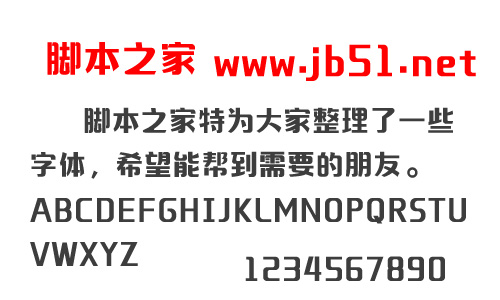
字心坊紳士黑字體
字心坊紳士黑字體是一款剛?cè)岵?jì)的粗黑體。設(shè)計(jì)初衷是一款力量感較強(qiáng)的同時(shí)還要有時(shí)尚美感。筆畫(huà)橫豎平直,刃器鋒口;拐角圓潤(rùn),點(diǎn)撇絲滑。既有剛毅之軀,也有柔和之美,歡迎喜歡字心坊紳士黑體的朋友前來(lái)下載使用。